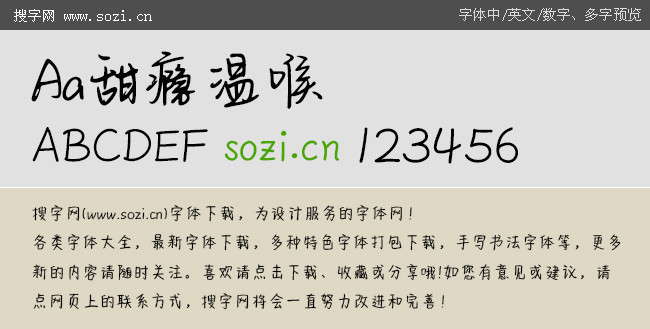
Aa甜癮溫喉
搜字網(wǎng)給大家提供一款A(yù)a甜癮溫喉中文字體下載,這是一款手寫風(fēng)格的書法字體,字體書寫流暢,字形瀟灑大方,適合海報(bào)設(shè)計(jì)、畫冊(cè)等宣傳廣告等應(yīng)用(此字體為個(gè)人非商用版,如需商用請(qǐng)聯(lián)系作者購(gòu)買版權(quán))。